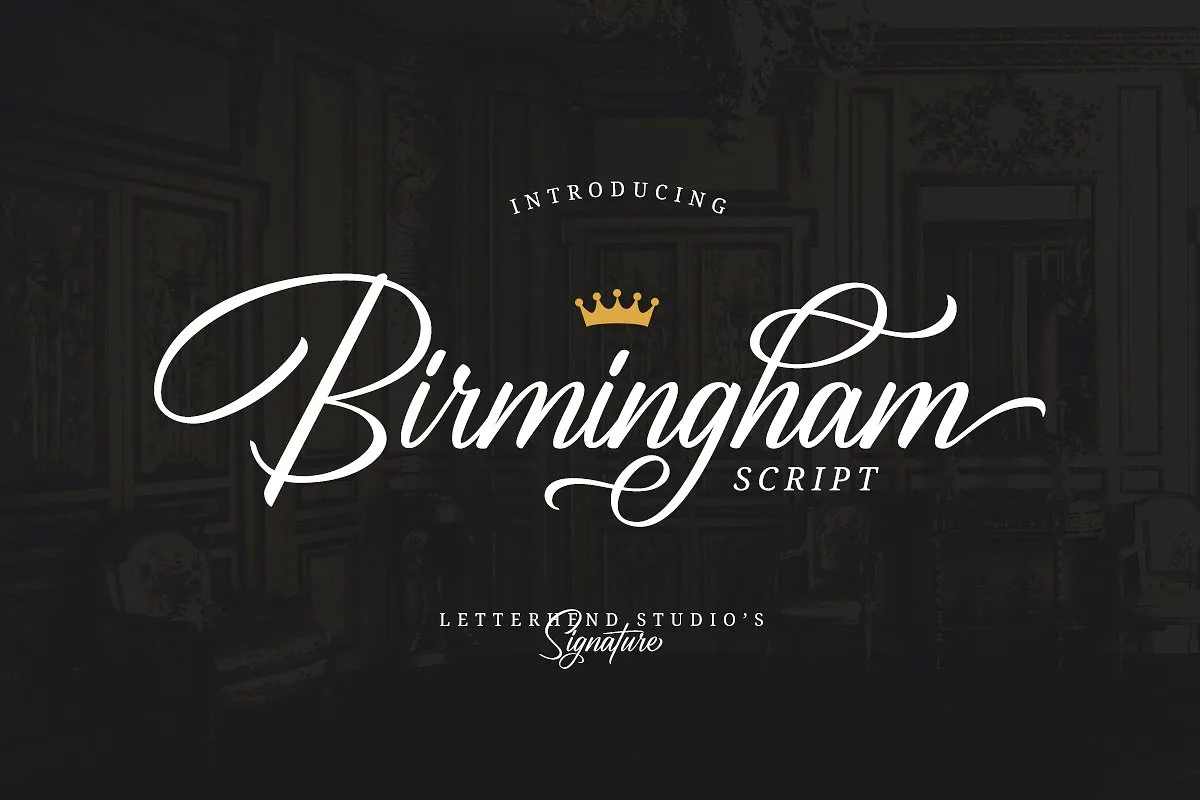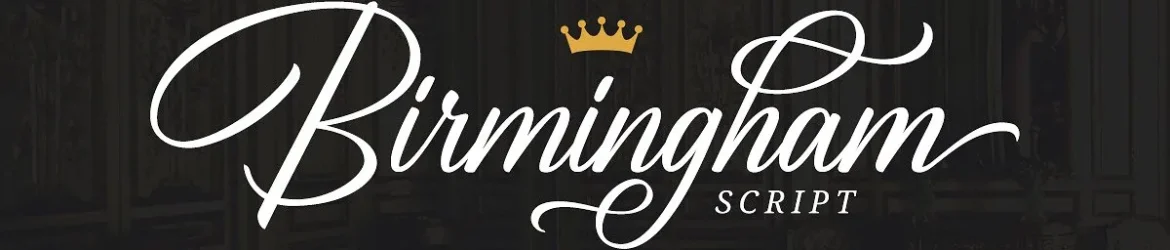
Birmingham Script Font – Download Grátis
A Birmingham Script Font é uma nova assinatura script que traz uma sensação fresca e elegante ao design. Feita pelo Designer Letterhend, esta fonte está disponível para download para designers de gráficos e criadores de imagens digitais. Com sua ampla gama de alternativas, o Birmingham Script Font é um recurso versátil que pode ser usado para criar logotipos para marcasagem, estilos de moda elegantes, convites de casamento ou até mesmo assinaturas autênticas. Com a presença de letras minúsculas e maiúsculas, símbolos e suporte multi-idioma, esta fonte traz um toque sofisticado que enriquece qualquer projeto gráfico em que seja aplicada. Perfecta para quem busca uma assinatura única e elegante para seus projetos de design, a Birmingham Script Font é uma escolha inspiradora para incorporar no seu arsenal de fontes.